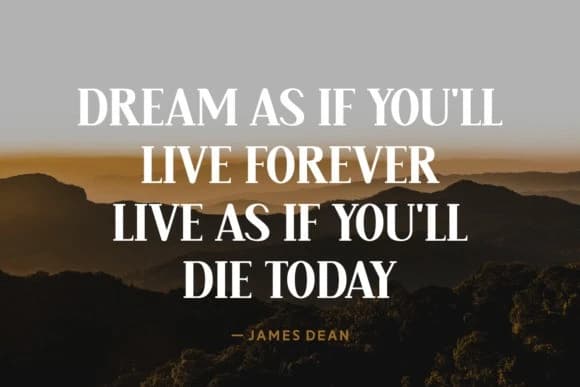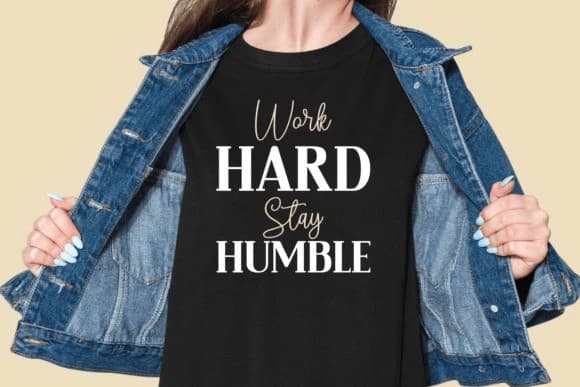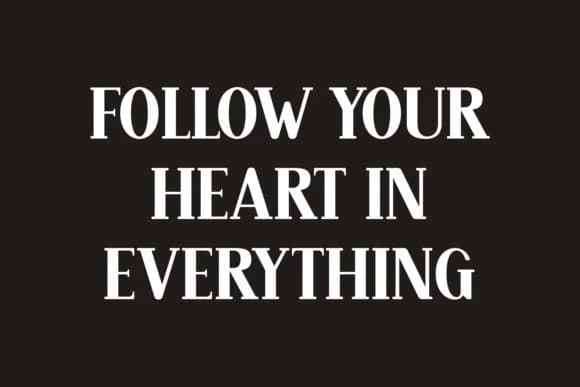
Fantastic Emosional Font – serif ile zarafetin uyumlu bir birleşimi, modern bir estetikle herhangi bir ortamı zenginleştirmek üzere tasarlandı. Özgün çekiciliği, fotoğrafçılığınıza, giyim ürünlerinize ve estetik markalaşmanıza vurgu katmak için idealdir.
Fantastic Emosional Font – serif ile zarafetin uyumlu bir birleşimi, her ortamı zenginleştirmek için tasarlanmış modern bir estetik sunuyor. Onun özgün çekiciliği, fotoğrafçılığınıza, giyim ürünlerinize ve estetik markalaşmanıza vurgu katmak için en uygun hale getirir.